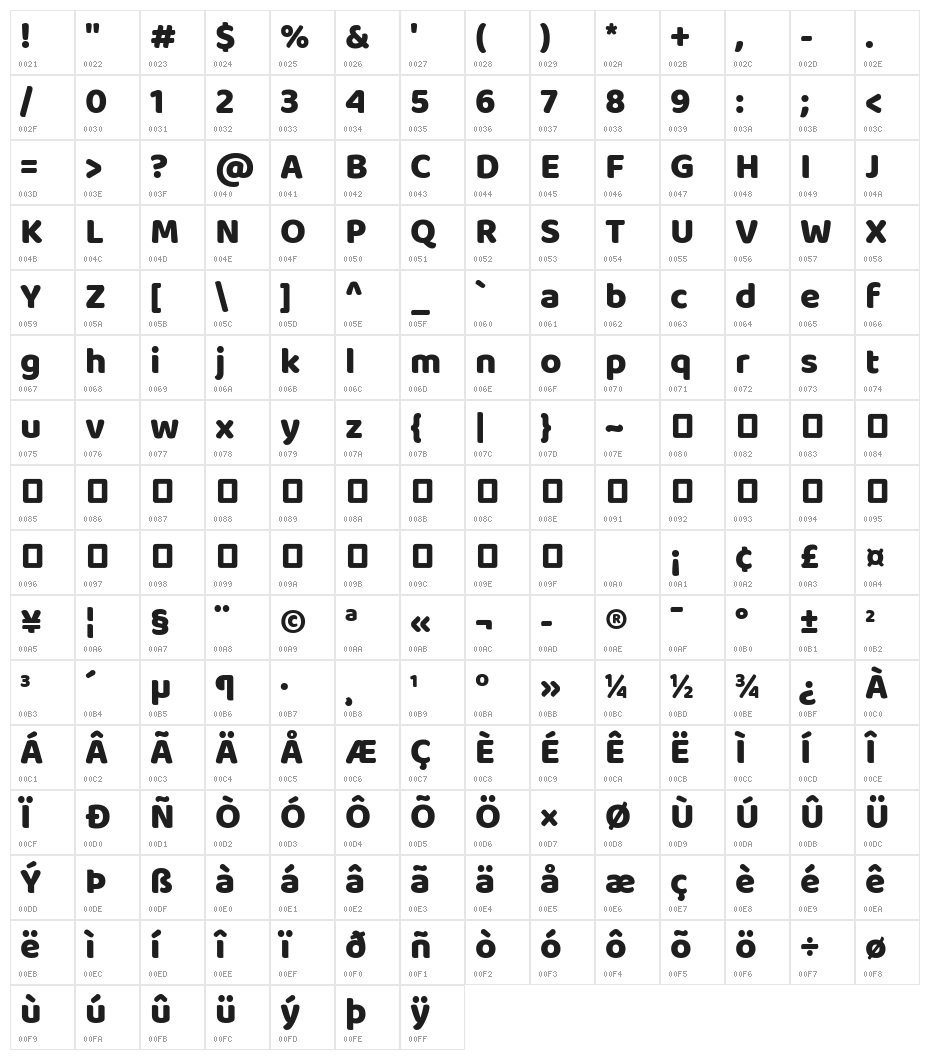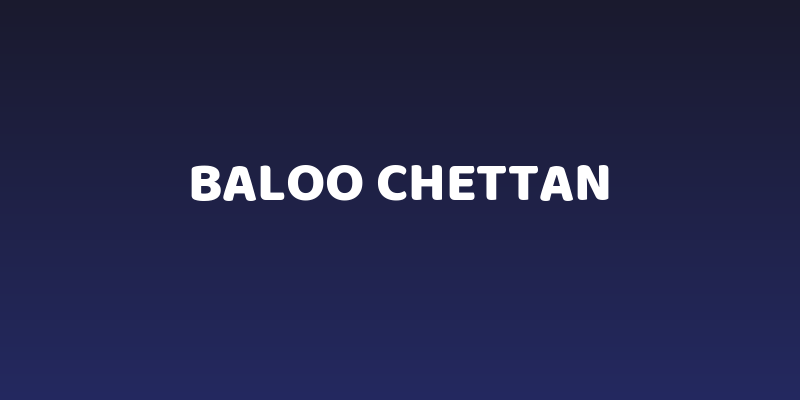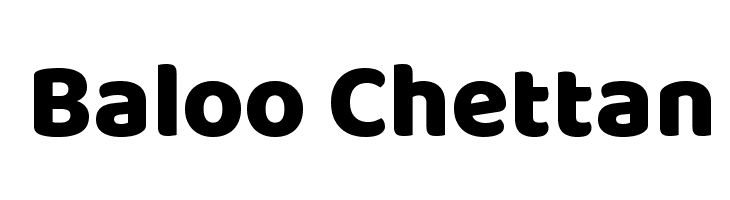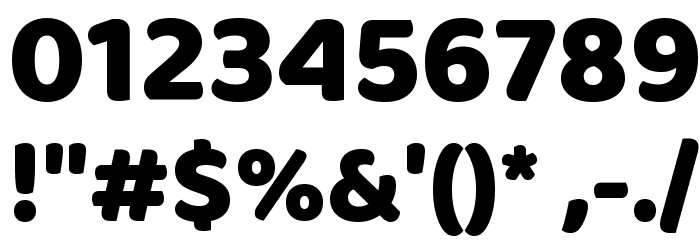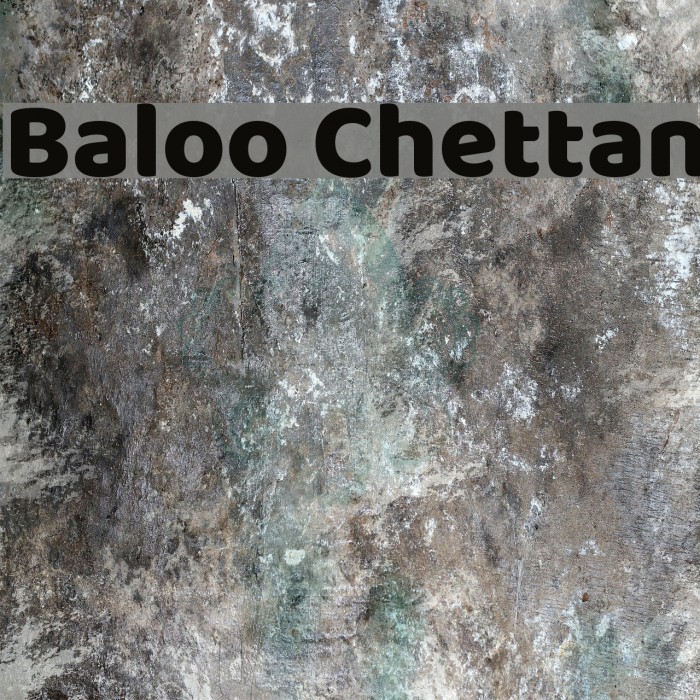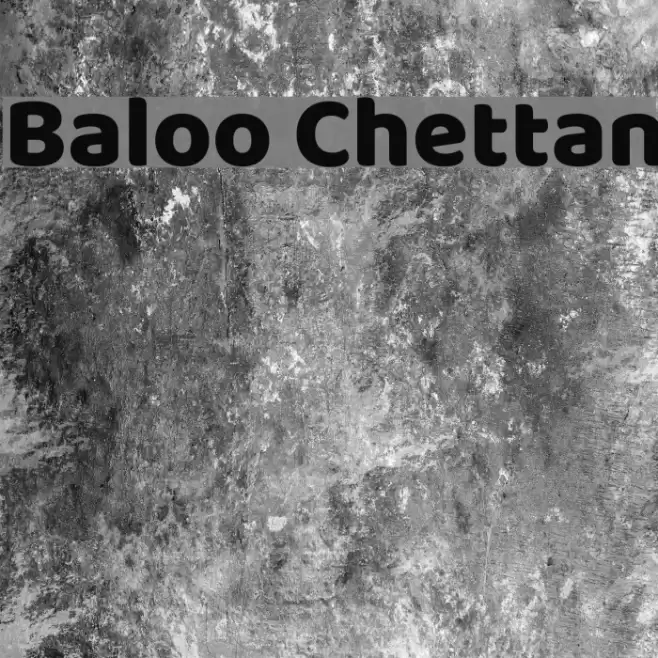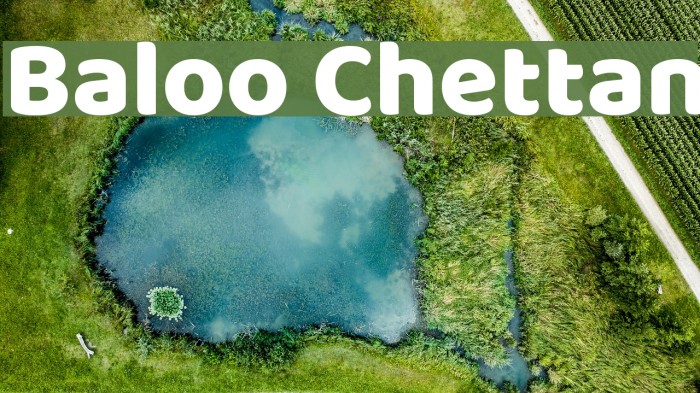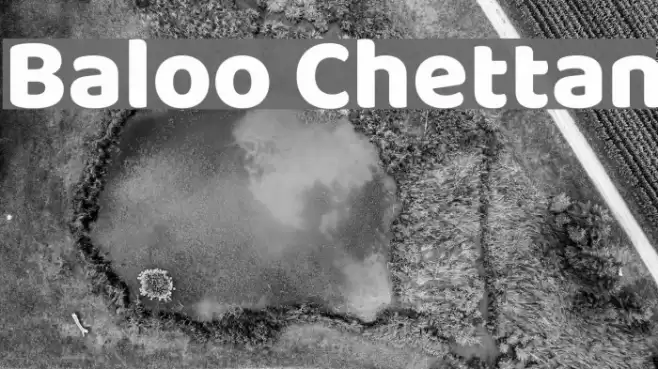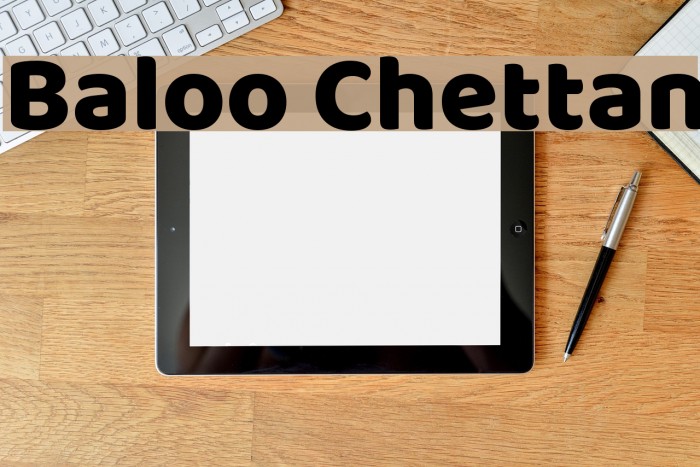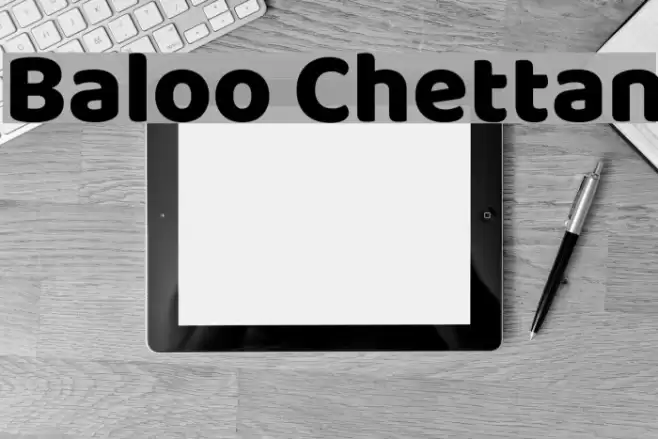
Baloo Chettan Font
| Style général | Playful |
| Cas d'utilisation | Headlines, Logos, Informal Text |
| Projets proposés | Ideal for children's books, playful branding, casual invitations, and educational materials. |
Baloo Chettan